Венгерские ő и ű в рукописном шрифте: как нарисовать двойной акут и проверить пару
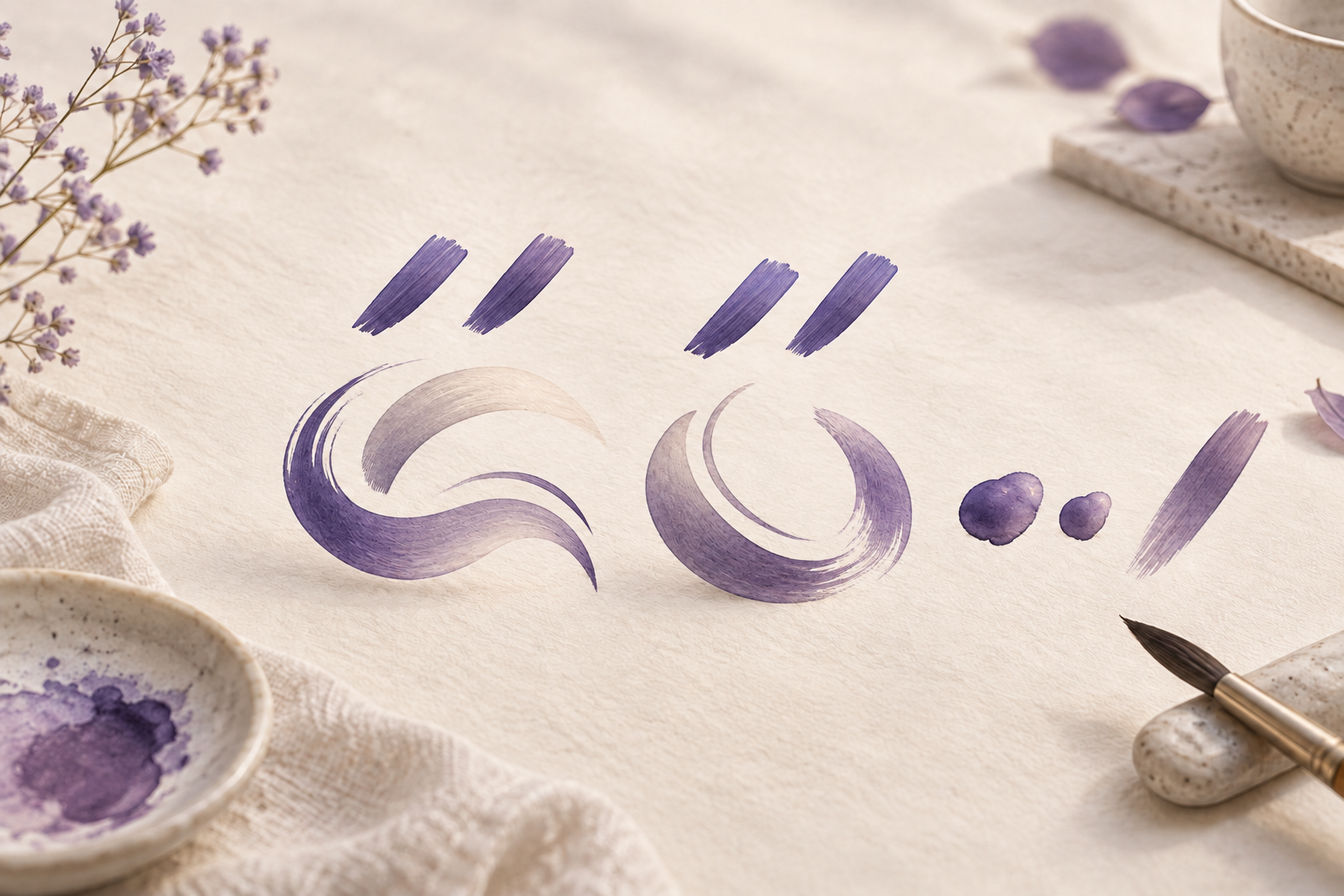
Венгерские ő и ű легко пропустить в тесте латиницы: они похожи на о и у с необычной «шапкой», но требуют отдельного рисунка и аккуратного размещения двух наклонных штрихов. В этом руководстве разберём, как построить пары строчных и прописных букв, не превратить двойной акут в умлаут, проверить текст в словах и отличить проблему рисунка от отсутствующего символа или сбоя кодировки.
Чем ő и ű отличаются от ö, ü, ó и ú
Венгерские ő и ű — самостоятельные буквы латинского набора с двойным острым акцентом. В той же системе полезно проверять их короткие пары ö и ü, а также буквы ó и ú с одним острым акцентом. Для дизайнера это не упражнение в подсчёте диакритик: в строке читатель должен различать тип знака и основу, а рисунок не должен случайно подменять одну букву другой.
В названиях символов Unicode прописная Ő обозначена как LATIN CAPITAL LETTER O WITH DOUBLE ACUTE, строчная ő — LATIN SMALL LETTER O WITH DOUBLE ACUTE; аналогично устроена пара Ű/ű. Комбинируемый знак U+030B называется COMBINING DOUBLE ACUTE ACCENT. Эти имена помогают сверить, какие именно символы попали в тестовый текст, но не задают единственно правильную форму ручного рисунка. Сверяйте кодовые точки с официальными списками Unicode для латинского расширения и комбинируемых диакритик.
Практическая задача — сделать так, чтобы две наклонные черты читались как пара, а не слипались в широкую крышу, не превращались в два вертикальных штриха умлаута и не выглядели отдельными кавычками. При этом базовая буква сохраняет собственную конструкцию: у ő акцент сидит над о, у ű — над у, а не над воображаемым общим овалом.
Сначала соберите короткий тест, потом рисуйте
До правки букв выпишите четыре контрастные пары: o–ö–ő–ó и u–ü–ű–ú. Затем добавьте прописные варианты O–Ö–Ő–Ó и U–Ü–Ű–Ú. Такой короткий ряд показывает, работает ли знак как система: одинаково ли устроен акут, как меняется ширина, остаётся ли достаточное пространство над прописными и различается ли двойной акут с умлаутом при быстром просмотре.
Проверяйте формы в двух режимах. Сначала поставьте символы рядом, чтобы сравнить детали; затем уберите ряд и прочитайте слова, где акцент встречается внутри обычного текста. Для венгерского подойдут, например, короткие слова и имена, содержащие ő или ű, а также вымышленные сочетания вроде «bő», «fű» и «hű». Важно сохранить сами диакритические буквы, а не подменять их похожими знаками из другого алфавита. В отдельной строке повторите их рядом с обычными латинскими глифами: «a e i o ö ő ó u ü ű ú m n r s t».
Не ограничивайтесь строкой символов. Поднимите, опустите и уплотните текст в макете, оставив обычные латинские буквы вокруг. В строке двойной акут сталкивается с верхним пространством соседних букв, строкой над ним, диакритиками соседних слов и краем текстового блока. Так легче заметить, что по отдельности аккуратные глифы в связном наборе становятся тесными или ритмически выпадают.
Постройте двойной акут как пару, а не как один широкий знак
Начните с базовой строчной o или u, уже согласованной с остальными круглыми и узкими буквами рукописного алфавита. Отметьте её визуальный центр и высоту верхней зоны. Затем нарисуйте две отдельные наклонные черты. Сравните их длину, толщину и угол между собой: знак должен выглядеть собранным, но просвет между чертами не должен пропадать в выбранном размере.
Не копируйте автоматически угол обычного акцента из é или ó. Рукописный жест может быть общим, но в двойном знаке важны две читаемые вершины и единая направленность. Если черты расходятся или сходятся без системы, знак выглядит как случайная галочка. Если они стоят слишком близко, после уменьшения превращаются в пятно; слишком широкий интервал, напротив, создаёт впечатление двух независимых элементов, не связанных с одной буквой.
Проверьте штрихи отдельно от основы на временной увеличенной копии. Эта проверка нужна только для диагностики: окончательное решение принимайте при обычном чтении. В сильном увеличении удобно сравнить концы, наклон и расстояние между чертами; в строке — оценить, узнаётся ли ö/ü, ő/ű и ó/ú без разглядывания. Не настраивайте глиф по единственному увеличенному фрагменту.
У строчной o и строчной u верхняя зона разная. Не переносите пару акутов между ними копированием без проверки. У овалоподобной о центр устойчив, но над узкой у две черты могут зрительно давить на букву или уходить к одному краю. Сначала согласуйте общую модель пары, затем при необходимости поправьте её положение, ширину или угол для каждой основы, сохранив узнаваемый семейный почерк.
Согласуйте прописные Ő и Ű со строчными
Прописная буква требует больше места над корпусом, но это не означает, что акут надо просто удлинить или раздвинуть. Сравните Ő с O, Ö и Ó, а Ű с U, Ü и Ú. Пара должна быть заметно связана со строчными, однако пропорции и расстояния могут меняться с учётом ширины прописной и масштаба рисунка.
Особенно внимательно проверьте верхний край тестовой строки. Если прописная с двойным акутом торчит существенно выше остальных, это может нарушить визуальное выравнивание строки. Сначала сравните реальные верхние границы глифов и ритм чередования, потом решите, нужно ли компактнее разместить пару или изменить её длину. Не прижимайте знак к букве только ради общей высоты: тесный интервал превращает две черты в нечёткую крышу.